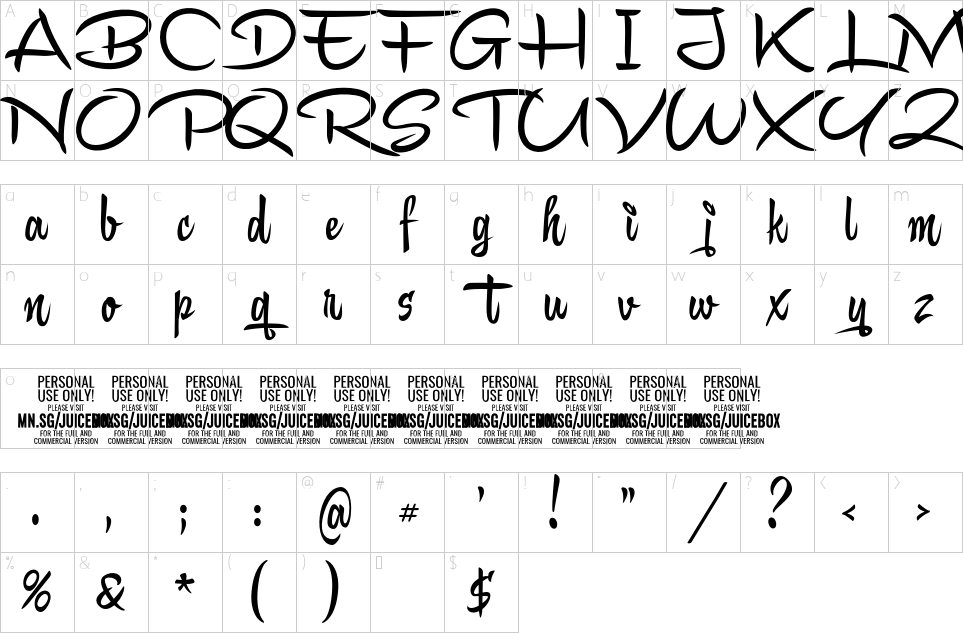
Juicebox Script Font | 1001 Free Fonts – Fonte Grátis
A fonte Juicebox Script é uma elegante e sofisticada escolha para aqueles que buscam uma fonte de script que combina facilmente alegria e elegância. Desenvolvida pelo designer Måns Grebäck, essa fonte é perfeita para criações digitais que necessitam de um toque de graça e uma aparência mais profissional. Seja para o design de blogs, a criação de materiais educacionais ou até mesmo o desenvolvimento de software, Juicebox Script oferece a capacidade de criar design gráfico que é tanto criativo quanto funcional. Com uma facilidade de download para computadores Windows e Mac, esta fonte gráfica está disponível para todos que buscam uma fonte moderna e versátil.